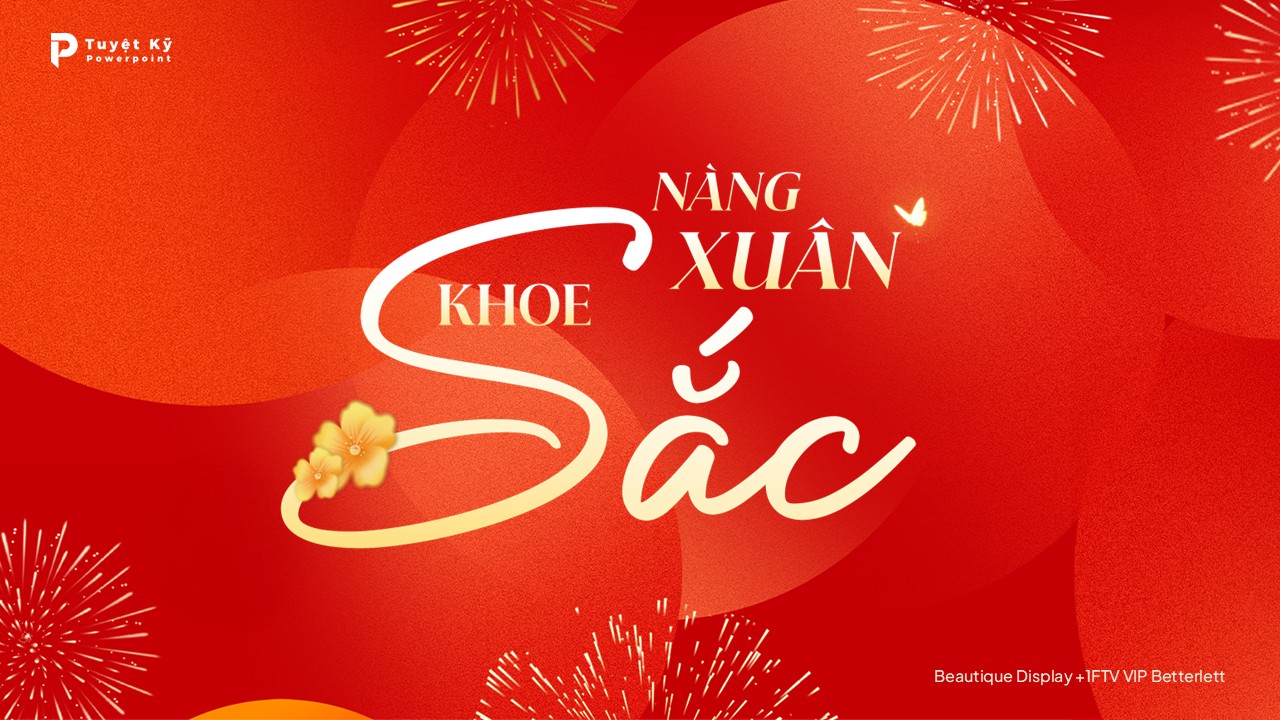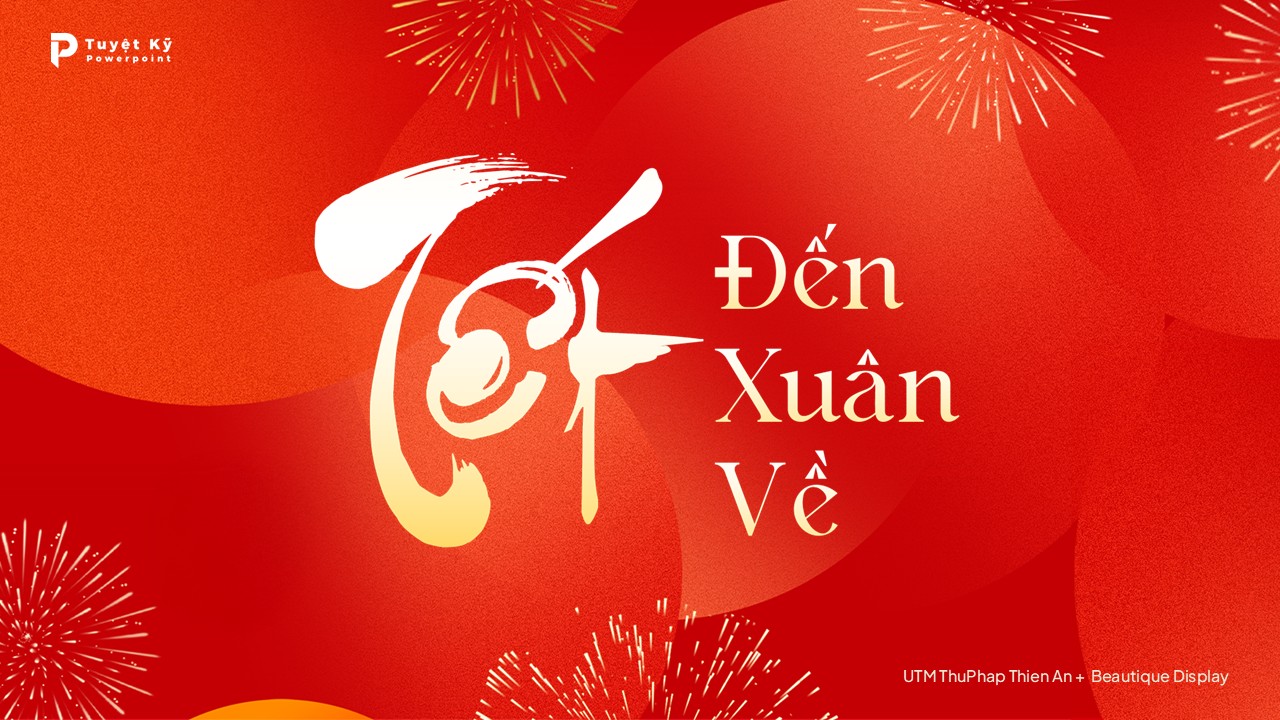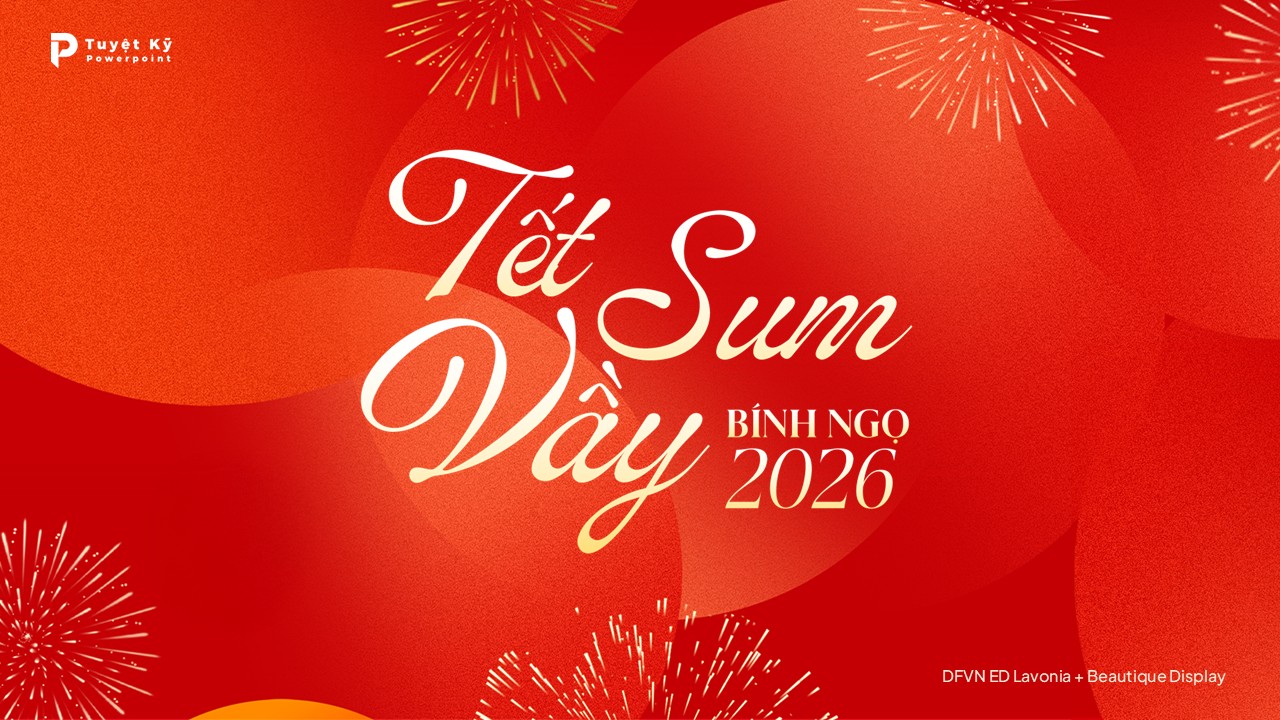
6 Combo Font chữ Tết 2026 – Typography Bính Ngọ tràn đầy sắc xuân
Tết 2026 đang đến gần, và xu hướng typography năm nay không còn là việc dùng một font đơn lẻ nữa. Thay vào đó, các designer chuyên nghiệp đang chuyển sang kết hợp nhiều font chữ để tạo nên thiết kế có chiều sâu, phân cấp rõ ràng và vẫn giữ được tinh thần Tết truyền thống nhưng hiện đại.
Một combo font được kết hợp khéo léo sẽ giúp mẫu slide Tết, thiết kế banner Xuân Bính Ngọ của bạn nổi bật hơn hẳn. Bài viết này sẽ chia sẻ 6 combo font chữ Tết đã được chọn lọc và kết hợp sẵn, bạn có thể áp dụng ngay cho poster, mẫu PowerPoint, social media và nhiều dự án khác.
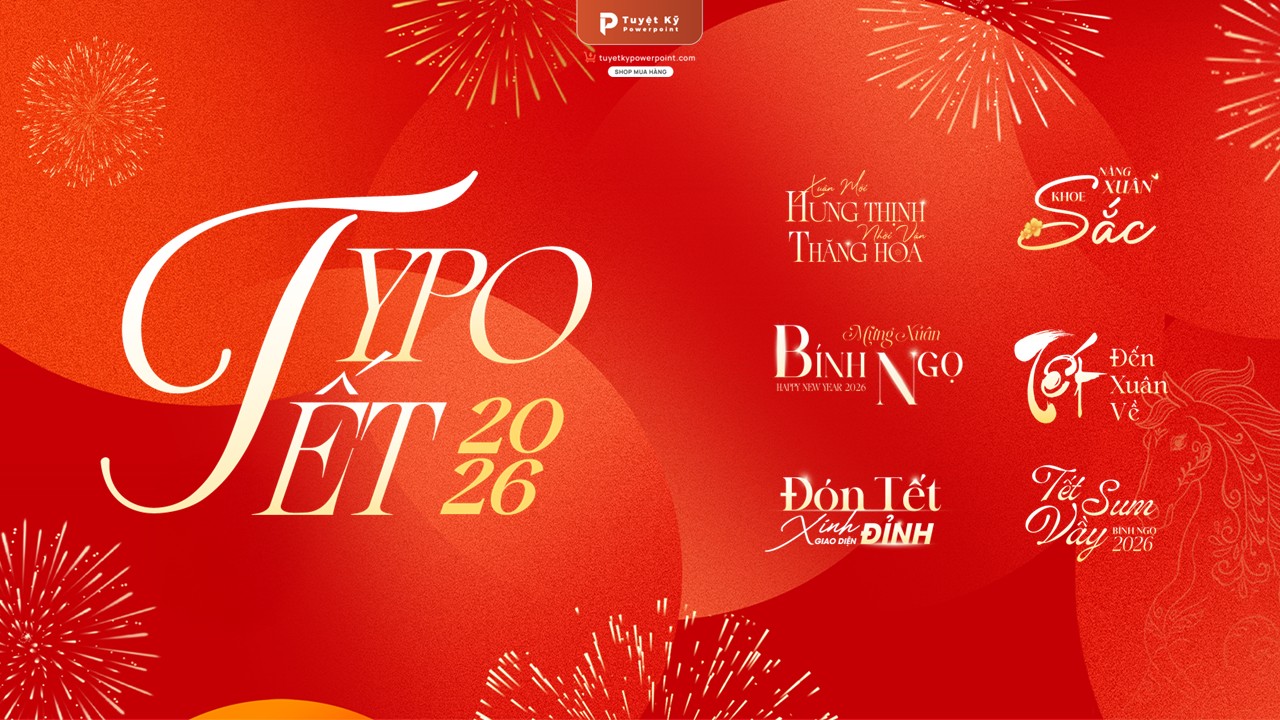
Tổng hợp Typography Tết Bính Ngọ 2026
1. Combo 01: DVFN Photograph + DVFN New Eddy
Typo “Xuân mới hưng thịnh – Thời vận thăng hoa”
Giới thiệu chung
Thiết kế typographic trong hình là sự kết hợp tinh tế giữa không khí Tết truyền thống và tinh thần hiện đại, sang trọng. Tone đỏ chủ đạo tượng trưng cho may mắn, hỷ sự và khởi đầu mới, mang đến cảm giác rộn ràng, phấn khởi đặc trưng của ngày xuân. Hai font chữ DVFN Photograph và DVFN New Eddy được phối hợp khéo léo, giúp tổng thể vừa có điểm nhấn nghệ thuật, vừa giữ được sự rõ ràng, dễ đọc. Đây là phong cách chữ rất phù hợp cho các ấn phẩm chúc Tết, truyền thông đầu năm và thiết kế quảng cáo mang tính cảm xúc mạnh.
Vai trò từng font
- DVFN Photograph: Đóng vai trò font chữ trang trí, mang nét mềm mại, bay bổng và giàu cảm xúc. Phù hợp để thể hiện thông điệp chúc Tết, tạo sự ấm áp, gần gũi và mang hơi thở nghệ thuật thủ công.
- DVFN New Eddy: Là font chữ nhấn mạnh, có form chữ dày, rõ, mang tính trưng bày cao. Giúp làm nổi bật thông điệp chính như “Hưng Thịnh – Thăng Hoa”, tạo ấn tượng thị giác mạnh và dễ ghi nhớ.
Ứng dụng thiết kế
- Banner, poster chúc Tết doanh nghiệp, cửa hàng, thương hiệu.
- Ảnh bìa Facebook, Zalo, fanpage dịp Tết Nguyên Đán.
- Backdrop sân khấu, tiệc tất niên, sự kiện đầu năm.
- Ấn phẩm quảng cáo Tết cho bán lẻ, bất động sản, tài chính.
- Thiết kế social post truyền thông chiến dịch Tết.
Đánh giá
Sự kết hợp giữa DVFN Photograph và DVFN New Eddy mang lại một phong cách chữ Tết vừa truyền thống, vừa hiện đại, rất giàu cảm xúc và tính ứng dụng cao. Đây là lựa chọn lý tưởng cho các thiết kế muốn truyền tải thông điệp may mắn, phát triển và thịnh vượng trong năm mới, đặc biệt phù hợp cho các chiến dịch truyền thông và quảng cáo dịp Tết.
2. Combo 02: SVN - Heroe Pro + DFVN New Eddy Display + DFVN Kamerun
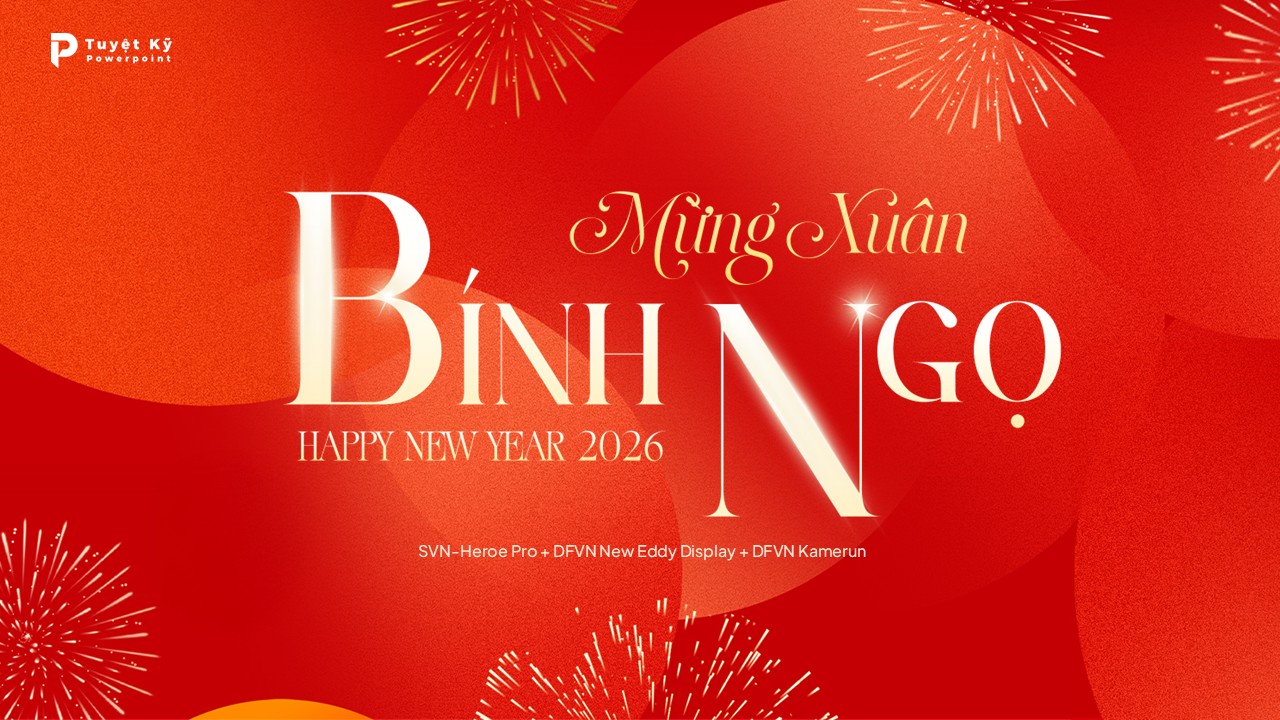
Typo “Mừng Xuân Bính Ngọ – Happy New Tear 2026”
Giới thiệu chung
Thiết kế typographic “Mừng Xuân Bính Ngọ – Happy New Year 2026” mang đậm tinh thần Tết cổ truyền Việt Nam, kết hợp hài hòa giữa sắc đỏ may mắn, hiệu ứng pháo hoa và bố cục chữ nghệ thuật hiện đại. Tổng thể thiết kế tạo cảm giác trang trọng, rực rỡ nhưng vẫn tinh tế, phù hợp cho các ấn phẩm chúc Tết đầu năm. Việc phối hợp nhiều font chữ khác nhau giúp phân tầng thông điệp rõ ràng, nhấn mạnh chủ đề năm mới, tạo điểm nhìn thu hút ngay từ ánh nhìn đầu tiên. Mẫu thiết kế không chỉ mang giá trị thẩm mỹ mà còn thể hiện không khí hân hoan, khởi đầu một năm mới nhiều may mắn và thành công.
Vai trò từng font
- SVN-Heroe Pro – “Mừng Xuân”: Đóng vai trò chữ dẫn dắt, tạo cảm giác hiện đại, gọn gàng và sang trọng. Font giúp mở đầu thông điệp nhẹ nhàng, tinh tế, cân bằng tổng thể bố cục.
- DFVN New Eddy Display – “Happy New Year 2026”: Là font nhấn mang tính trang trí cao, tạo điểm sáng thị giác và cảm xúc lễ hội. Phù hợp để thể hiện thông điệp chúc mừng năm mới nổi bật, rực rỡ.
- DFVN Kamerun – “Bính Ngọ”: Đóng vai trò chữ trung tâm, mang nét cổ điển – Á Đông, tạo chiều sâu văn hóa. Font giúp tên năm trở nên trang trọng, có điểm nhấn và giàu bản sắc Tết Việt.
Ứng dụng thiết kế
- Poster chúc Tết treo văn phòng, công ty, trường học
- Social post chúc mừng năm mới trên Facebook, Zalo, Instagram
- Slide mở đầu cho bài thuyết trình đầu năm
- Banner website, landing page dịp Tết
- Thiết kế backdrop mini hoặc standee trang trí Tết
Đánh giá
Sự kết hợp hài hòa giữa SVN-Heroe Pro, DFVN New Eddy Display và DFVN Kamerun đã tạo nên một thiết kế typographic Tết vừa hiện đại, vừa đậm chất truyền thống. Mẫu chữ không chỉ truyền tải trọn vẹn thông điệp “Mừng Xuân Bính Ngọ – Happy New Year 2026” mà còn giúp các ấn phẩm Tết trở nên chuyên nghiệp, nổi bật và giàu cảm xúc. Đây là lựa chọn lý tưởng cho mọi thiết kế chúc mừng năm mới cần sự tinh tế và ấn tượng ngay từ cái nhìn đầu tiên.
3. Combo 03: 1FTV VIP Coaster Simone + 1FTV VIP Betterlett + UTM Avo
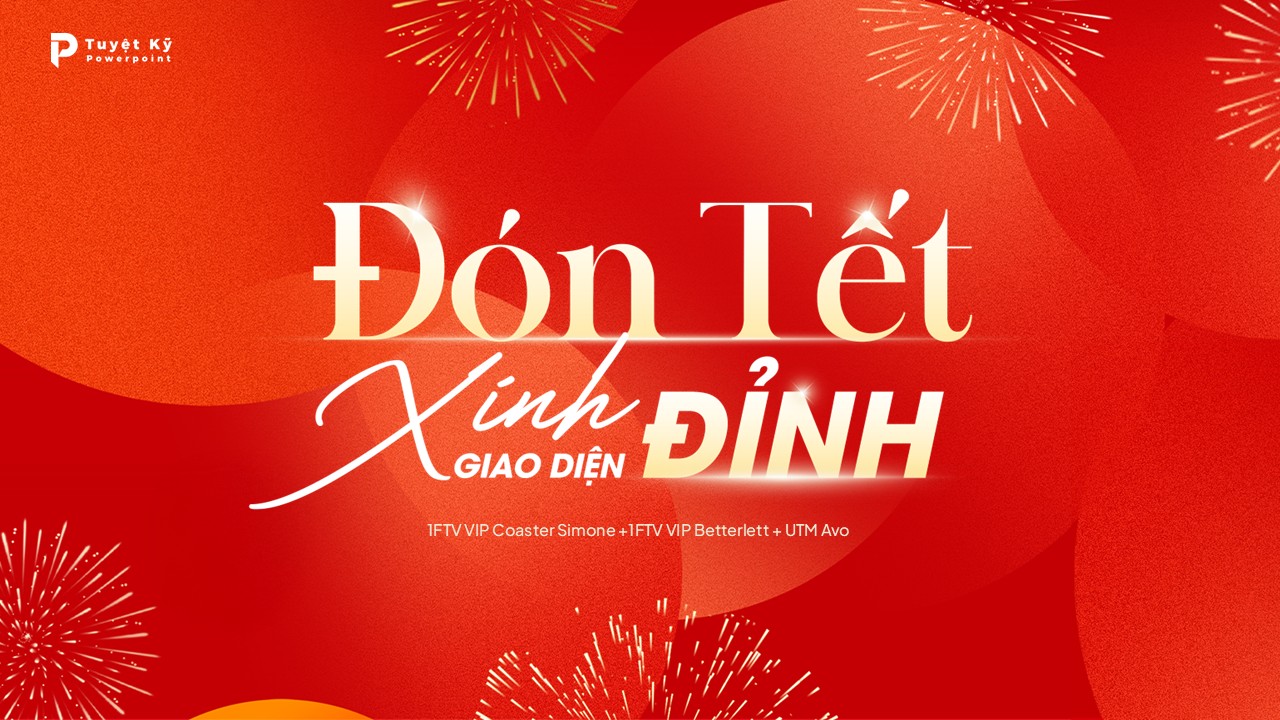
Typo “Đón Tết xinh – Giao diện đỉnh”
Giới thiệu chung
Thiết kế typographic “Đón Tết Xinh – Giao Diện Đỉnh” là sự kết hợp hài hòa giữa tinh thần Tết truyền thống và hơi thở thiết kế hiện đại. Bố cục chữ được sắp xếp có chủ đích, tạo nhịp điệu thị giác rõ ràng, giúp thông điệp nổi bật ngay từ cái nhìn đầu tiên. Tone đỏ chủ đạo gợi không khí sum vầy, may mắn, trong khi hiệu ứng chữ mềm mại và chắc chắn mang lại cảm giác sang trọng, chuyên nghiệp. Mẫu thiết kế phù hợp cho nhiều ấn phẩm truyền thông dịp Tết, vừa giữ được nét văn hóa Việt, vừa đáp ứng yêu cầu thẩm mỹ đương đại.